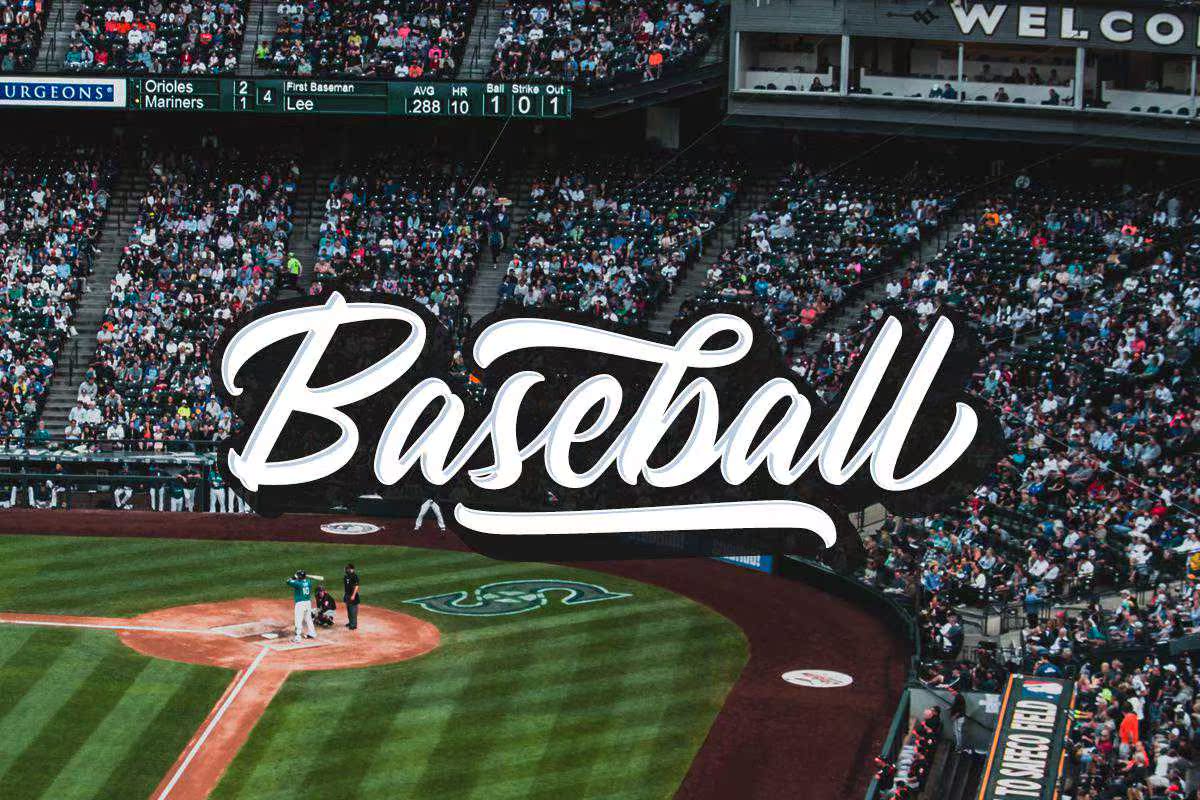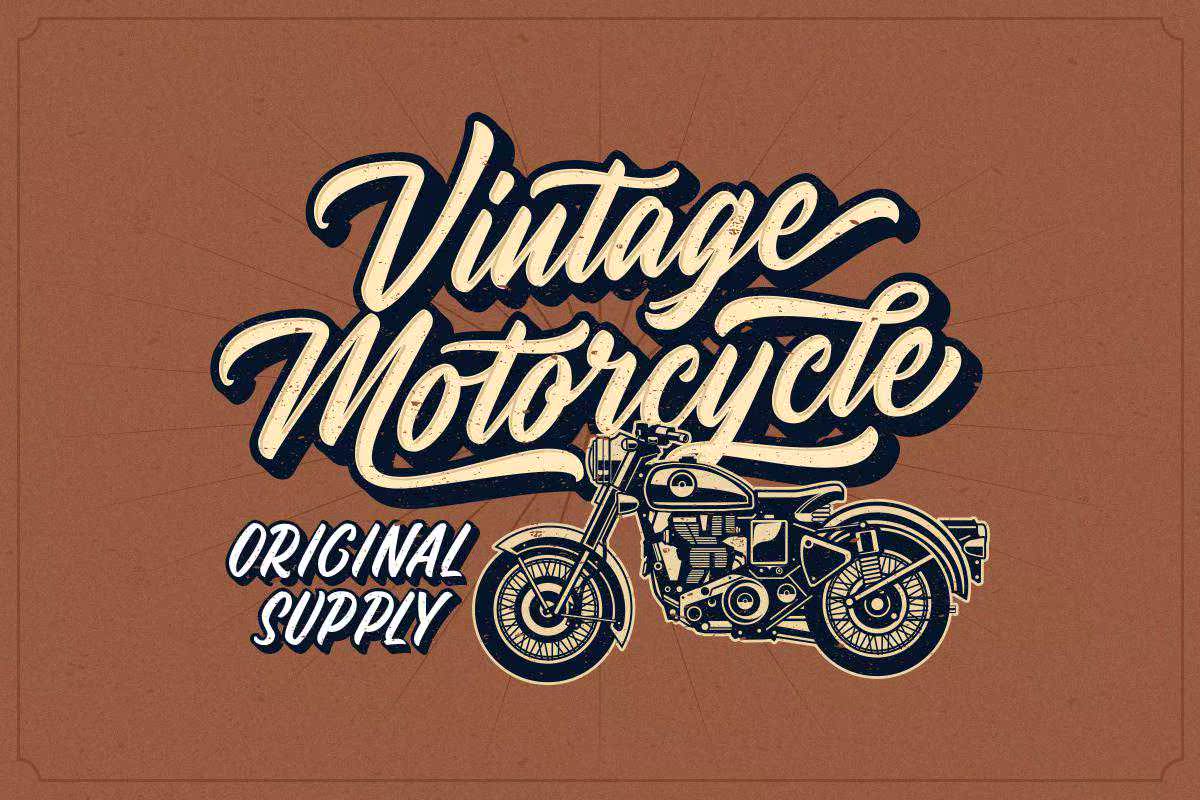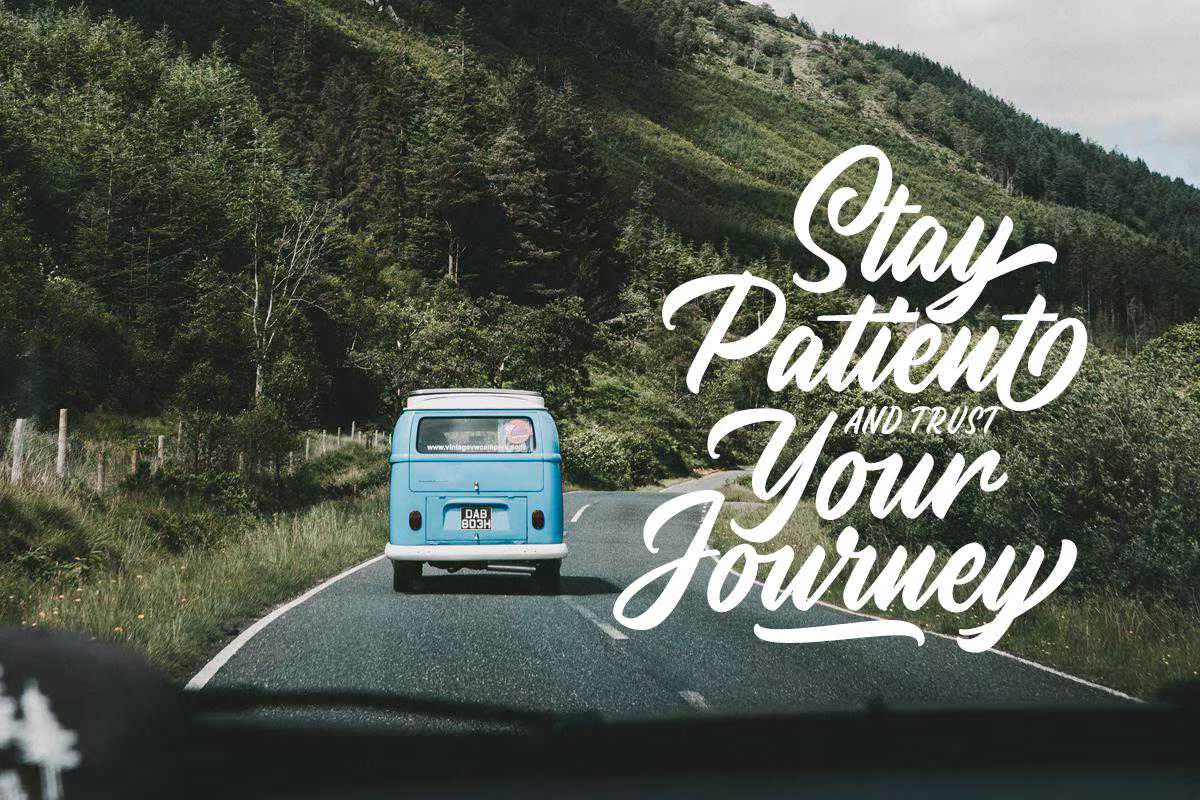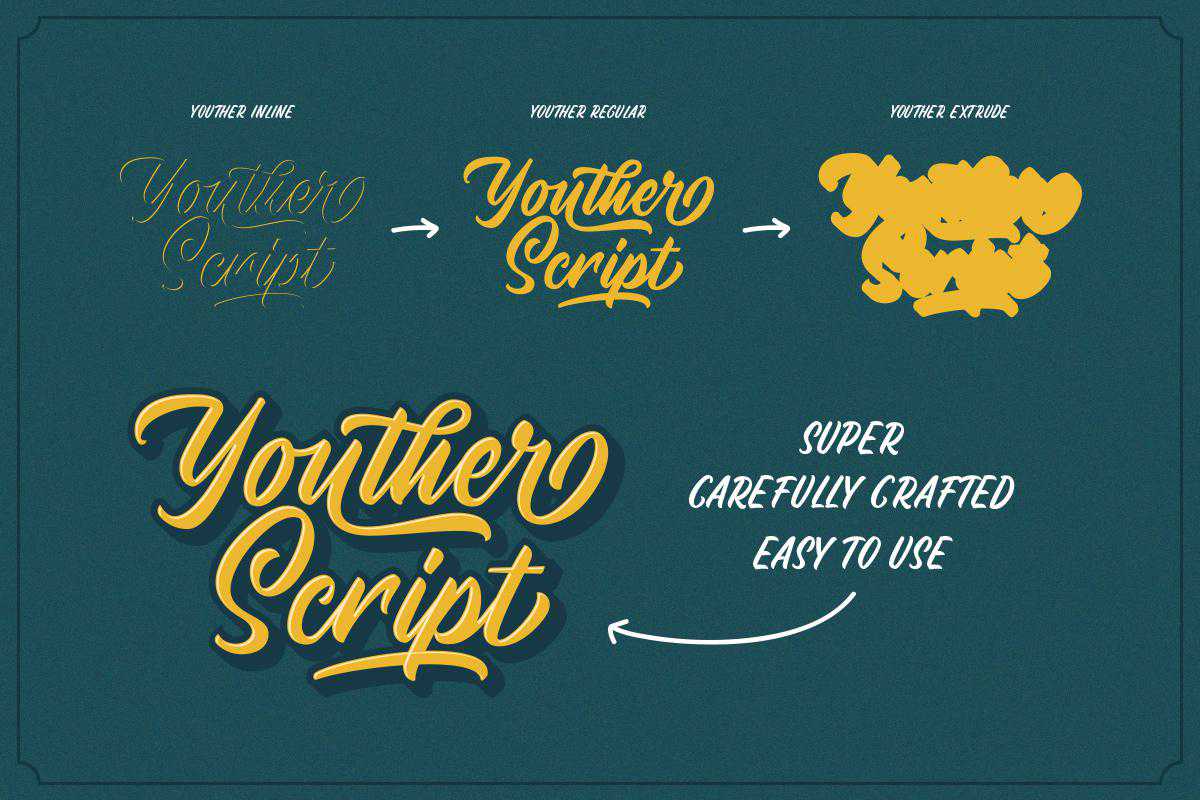
你是一个具有分层风格的字体。是的,你可以不用任何插件操作,用这种字体制作一个动画!此FontFamily使用Capsfont保存了精彩的脚本和密码。您完全可以使用密码、徽章和标签!这有许多五种类型的功能,包括:套用、风格替换、上下文替换、swash等,并支持多种语言。YouThere是一款具有分层风格的字体。是的,您可以使用这种字体制作一个动画,而无需任何插件操作!此FontFamily使用Capsfont保存了精彩的脚本和密码。您完全可以使用密码、徽章和标签!这有许多五种类型的特点:语言、文体交替、语境交替、华而不实等,并支持多种语言。